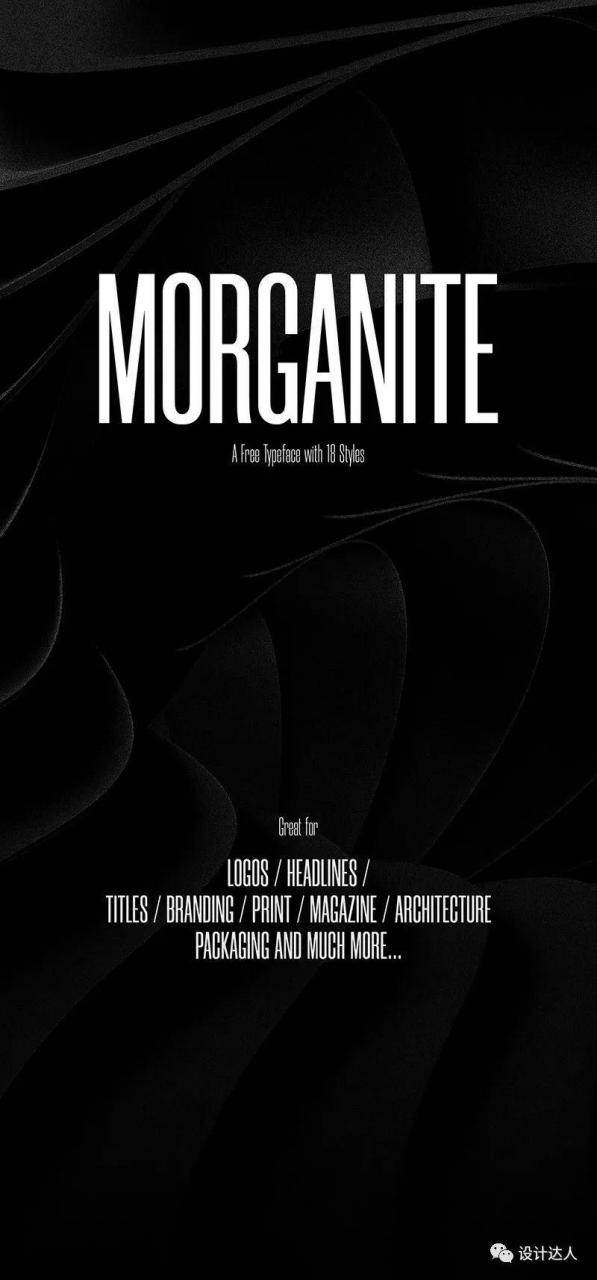
免费英文字体:Morganite
过去我们经常以字体包形式分享,但今天这款英文字体「Morganite」必须单独介绍,好让大家深刻知道这款字体的存在。该字体由印度UX/UI设计师 Rajesh Rajput 倾力打造,并且开放免费个人及商业用途。
不要以为 Morganite 只有26个英文字母,这套字一共18个风格,并且包含标点、符号、数字统一设计,是一款美丽而时尚的字体。
这么齐全的字体可见设计师非常用心制作,之于字体好不好看,用在什么风格?我想下面这些海报设计可以告诉你答案。
Morganite 免费字体是来自印度新德里的设计师Rajesh Rajput所设计,字体是免费的,意味着你可以自由地用于个人和商业,未经书面许可,不得修改字体文件,用于二次发售,这也是对设计师的尊重,字体包括18种风格,从细到粗,还有倾斜体,字体风格非常优美,适用于电商设计价格数字展示及电影海报设计,这款字体你值得拥有。